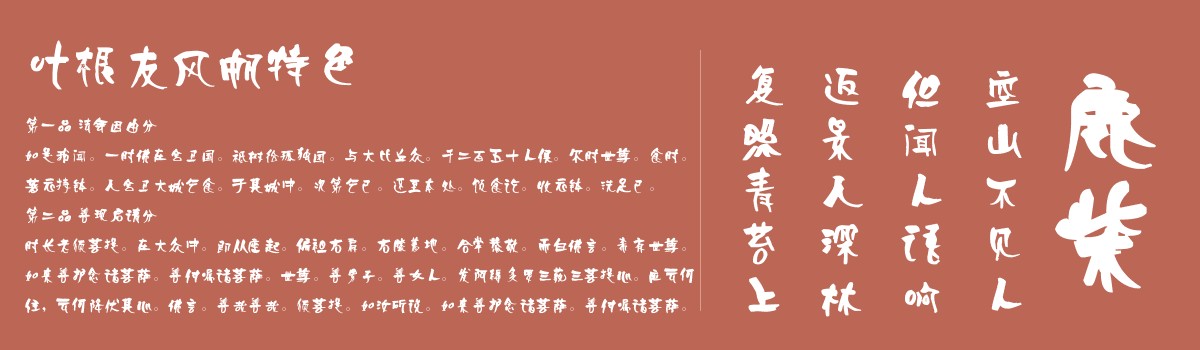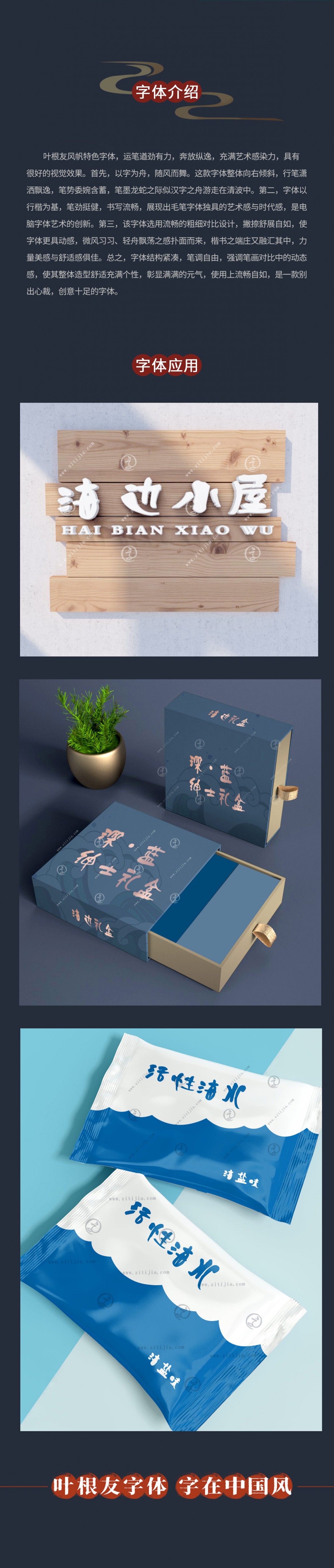
叶根友风帆特色
字体作者:叶根友
创作年代:2008年
字体字数:6763个中文汉字以及其他英文字母和阿拉伯数字
字体介绍
叶根友风帆特色字体是一款以帆船的造型来设计,风格独特,寓意深远,整个字体向右倾斜,字体富有更新的书法创新思维,不落俗套。在笔画对称学中属于是一种不走寻常思维的汉字字体创意,融合了中国书法黄金分割法则的侧重理念。